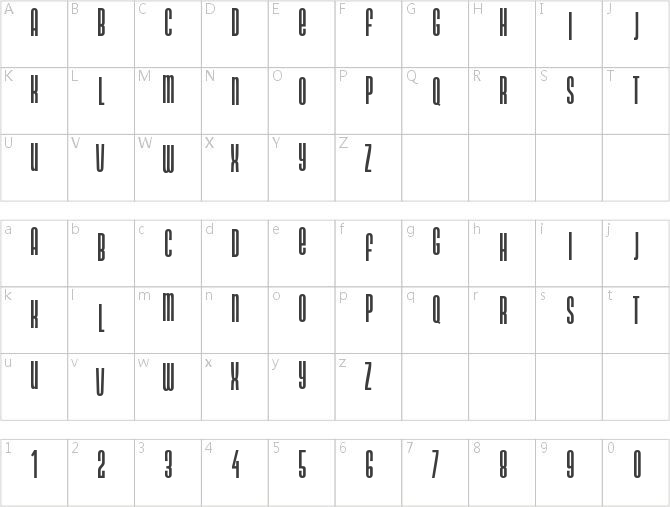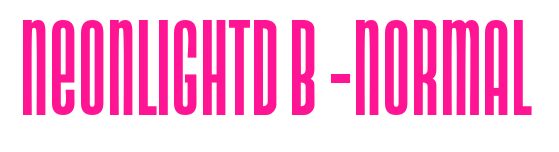
字體名稱: Neonlig
NeonlightDB-Normal
NeonlightDB-Normal介紹
NeonlightDB-Normal字體字庫是一款讓人賞心悅目、百看不厭的英文字體,適合各類廣告和產品包裝設計應用,字體大小0.05MB,格式為ttf字體,上傳用戶是W^xzj,作者/版權方為未知